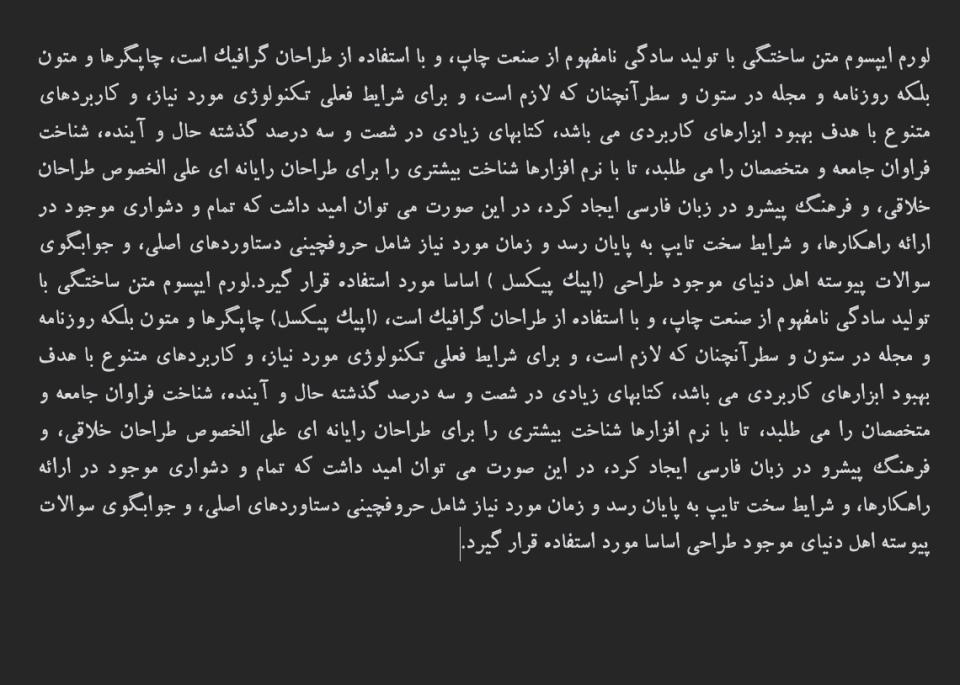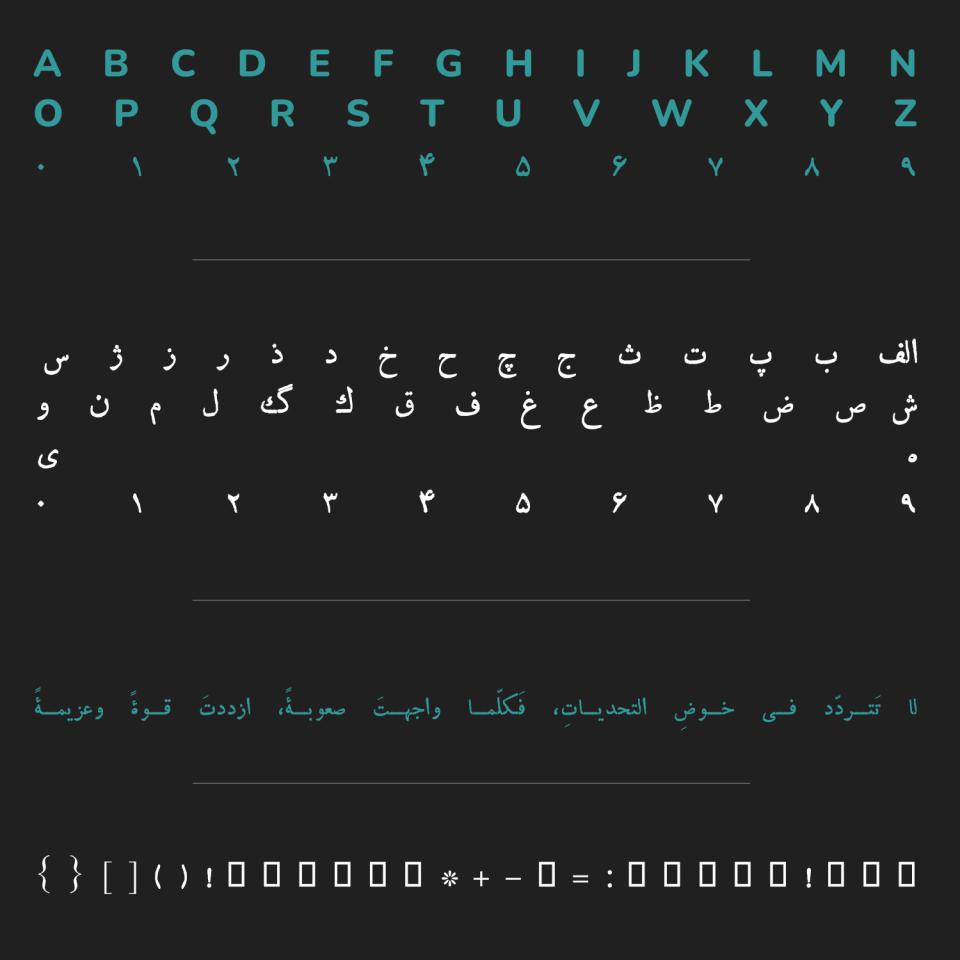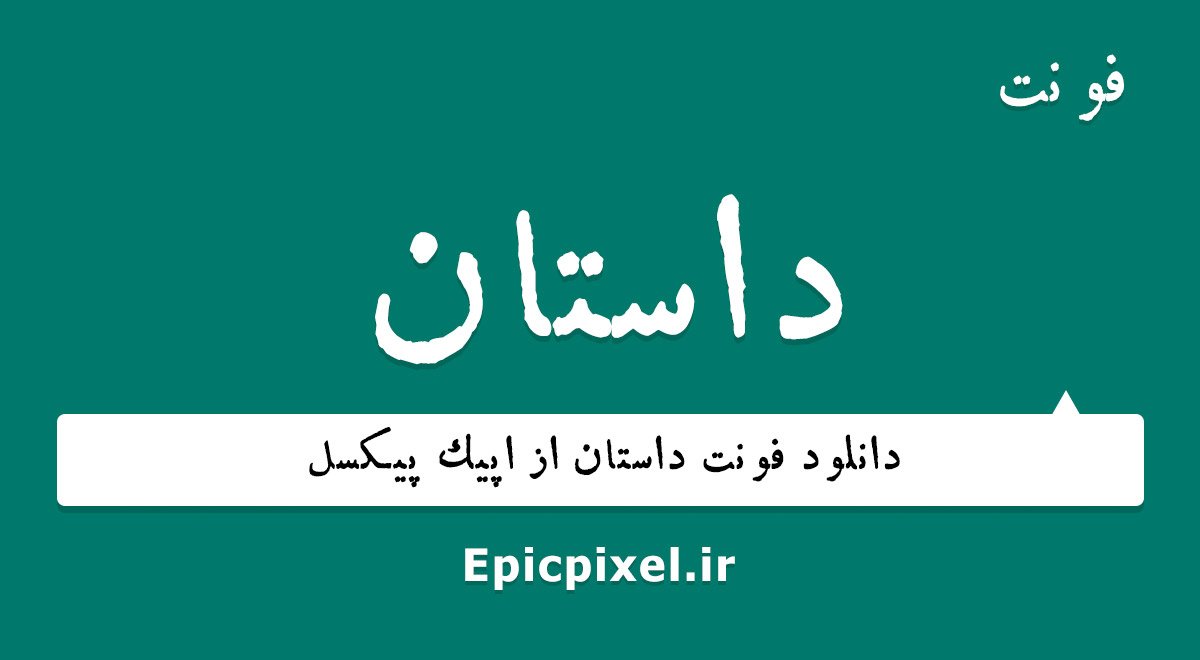
فونت فارسی داستان، با طراحی خاص و فانتزی اش، حسی نوستالژیک و صمیمی را به مخاطب القا می کند. این فونت که به صورت رایگان در دسترس است، برای طیف وسیعی از پروژه ها، از طراحی های گرافیکی گرفته تا استفاده در شبکه های اجتماعی، گزینه ای ایده آل به شمار می رود. فرمت ttf این فونت، سازگاری کامل با تمامی نرم افزارهای طراحی را تضمین می کند و به راحتی در سیستم عامل های مختلف قابل نصب و استفاده است.
یکی از ویژگی های برجسته فونت داستان، طراحی خاص حروف آن است که به نوشته ها جلوه ای منحصر به فرد می بخشد. این فونت با وجود ظاهر فانتزی اش، خوانایی مناسبی دارد و در اندازه های مختلف به خوبی قابل استفاده است. البته باید توجه داشت که شاید این سبک خاص، برای متون طولانی و رسمی چندان مناسب نباشد و بیشتر برای عناوین، نوشته های کوتاه و طرح های خلاقانه توصیه می شود. با این حال، رایگان بودن و سهولت استفاده از آن، فونت داستان را به انتخابی جذاب برای طراحان و کاربران عادی تبدیل کرده است. اگر به دنبال فونتی هستید که به طرح هایتان روحی تازه ببخشد، فونت داستان می تواند گزینه ای عالی باشد.